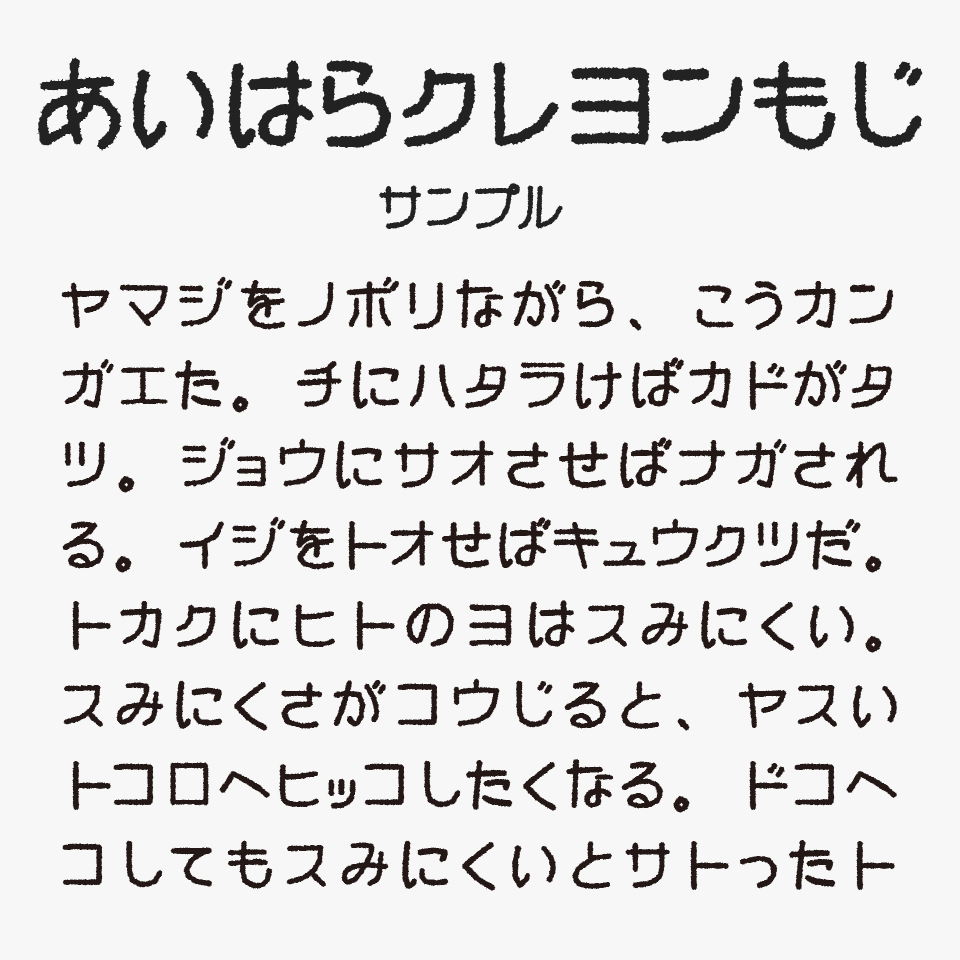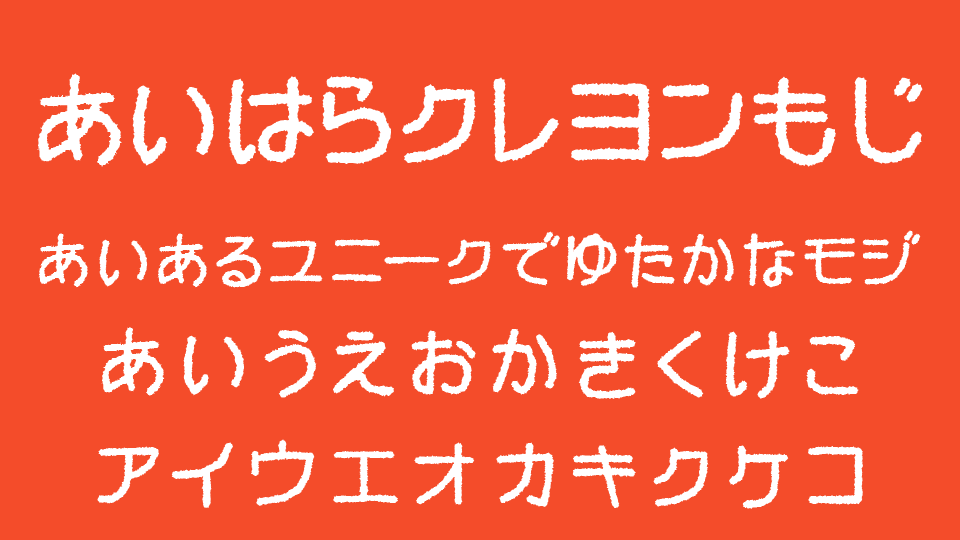
あいはらクレヨンもじフォントは、クレヨンで丁寧に書いたような、かすれと温もりを持つ可愛らしい手書き風フォントです。
線の輪郭がわずかにざらついており、紙の上に実際に描いたようなクレヨンならではの質感がデジタルの中にしっかりと表現されているフォントです。
絵本の本文や子ども向けのワークシート、手作り感を大切にしたZINEやポスターなど、人の手の温度を感じさせたい場面にぴったりです。